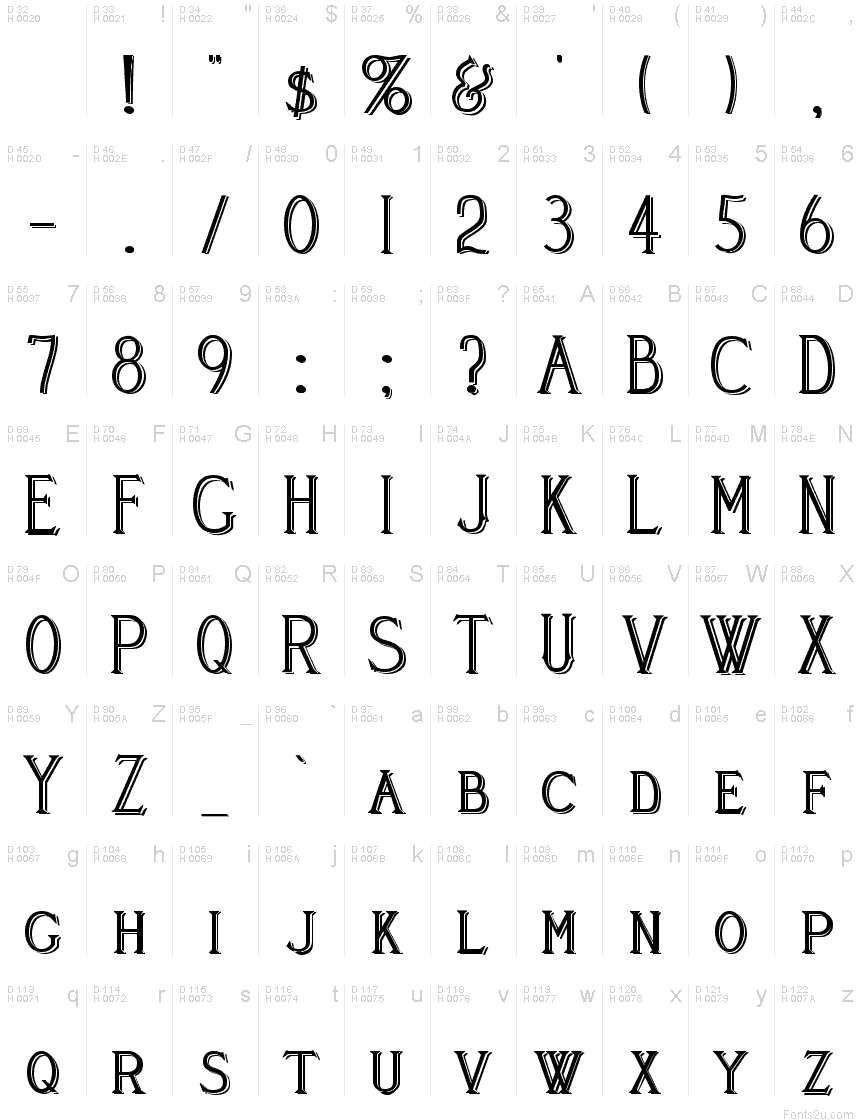
Cleaver's_Juvenia_Blocked
Cleaver's Juvenia Blocked od PJL to darmowy, dekoracyjny krój szeryfowy, który zamienia każde słowo w małe dzieło architektury. Wysokie, wąskie litery osadzone są w wyrazistych czarnych konturach z subtelnym wewnętrznym cieniem, co nadaje im efekt rytego napisu lub tłoczenia. Całość ma w sobie teatralny, lekko staroświecki sznyt — niczym szyldy z retro salonów gier — jednak dzięki korzeniom rodziny Dustismo, font pozostaje zaskakująco czytelny nawet przy dużym rozmiarze.
Z Cleaver's Juvenia Blocked nagłówki natychmiast zyskują wymiar bez potrzeby stosowania dodatkowych efektów czy pracy na warstwach. Ten darmowy font świetnie sprawdza się na okładkach książek, plakatach, retro ulotkach, tytułach gier, logotypach i opakowaniach tematycznych. Wygląda najlepiej, gdy tekst jest krótki i wyrazisty; warto wtedy zestawić go z prostym krojem bezszeryfowym w mniejszych rozmiarach, aby pozwolić tym rzeźbionym konturom i cieniom grać główną rolę.